Wortbild
Word Face
Der Begriff »Schriftbild« kommt vom erhabenen spiegelverkehrten Bild eines Schriftzeichens auf der Drucktype. Ein Wortbild kann ein Schriftzug sein, eine Marke, die einprägsam gestaltete Form eines Wortes. Erst per Hand, dann wahlweise digital, zeichnen wir Lettern für ein Wortbild Eurer Wahl, deren Bildhaftigkeit nicht festgelegt ist. Für den Sommer-Rundgang setzen wir sie dann gemeinsam in Szene.
The German term “Schriftbild” (type face) comes from the raised, mirror-inverted “image” of a character on a letterpress type cone. “Wortbild” refers to the lettering design of a word, be it on a sign or as part of a brand. Starting from hand-drawn lettershapes with the possibility to switch to digital drawing tools, we will design letters for a “word face” of your choice, with freedom in graphic quality. The results will be presented at our Summer Rundgang exhibition.
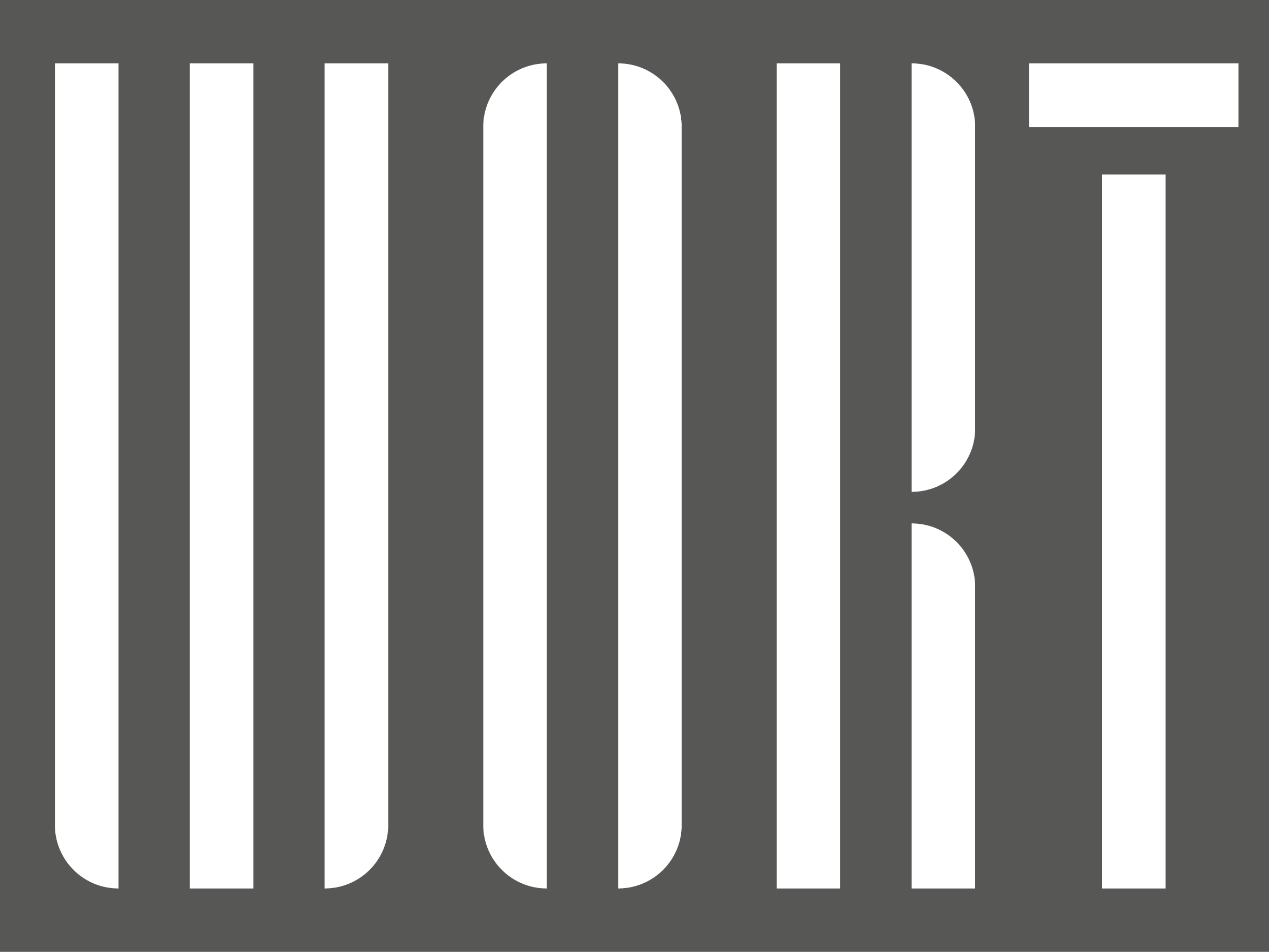
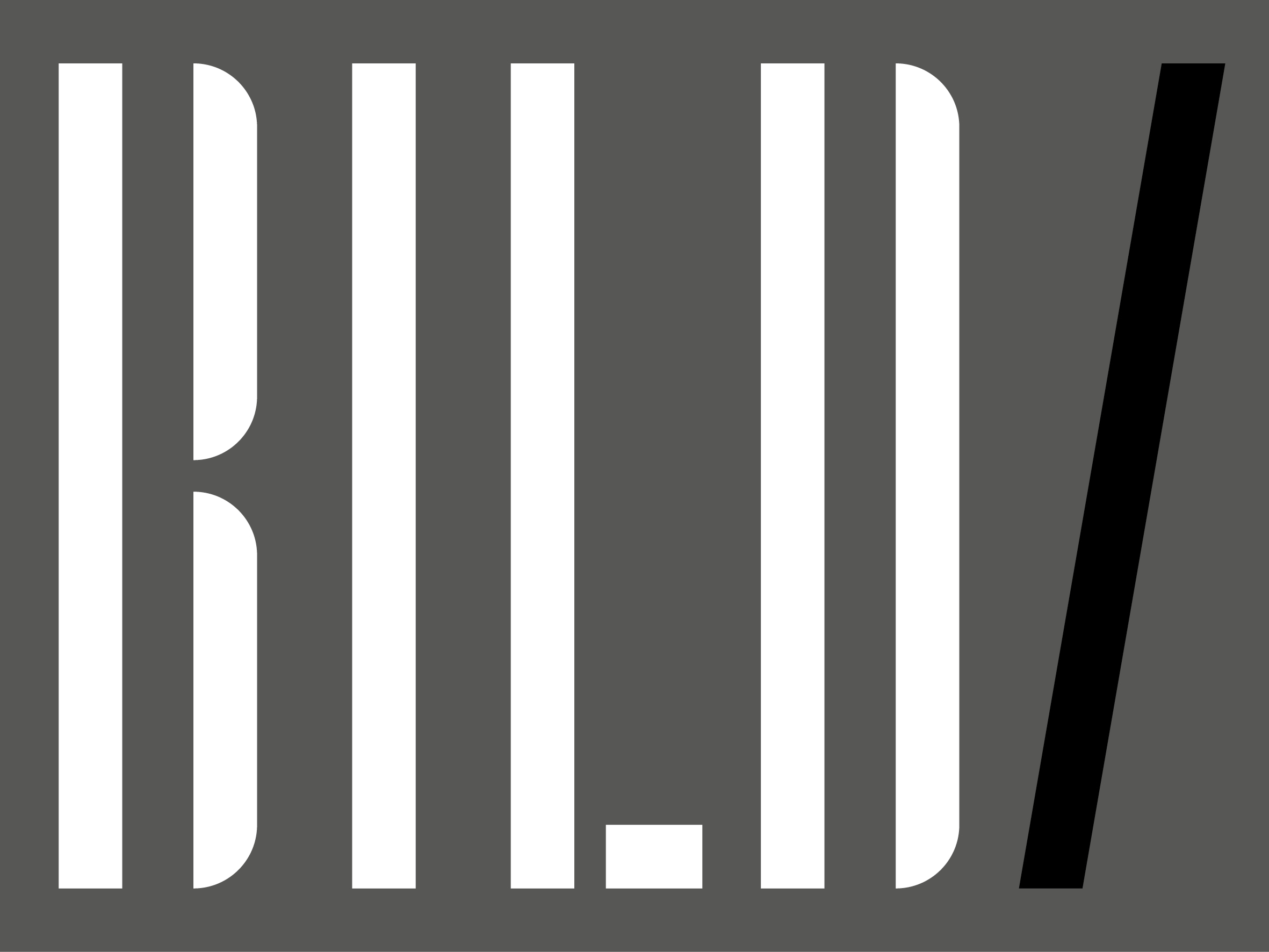
Typografische Selbstverwaltung (Typo-Club #19)
Typographic Self-Management (Typo Club #19)
Die Rolle des Lehrenden beschränkt sich in diesem Kurs auf das Fragenstellen, er darf nichts erklären, keine Antworten liefern – das ist den Studierenden überlassen. Je nach Anzahl der Teilnehmer*innen bilden sich kleine Gruppen, die selbstständig eine Einheit vorbereiten und präsentieren. Auch die praktische Aufgabe obliegt der Entscheidung der Studierenden. Es wird Protokoll geführt, eine Dokumentation der Veranstaltung erstellt und auf dem Rundgang präsentiert. Ziel ist eine genuin studentsiche Perspektive des Faches Typografie bei uns an der UdK Berlin.
The role of the teaching person is reduced to asking questions in this course, neither will he allow himself to explain anything or deliver any answers—that is left to the students. Depending on the amount of participants, small groups are formed who will prepare and present a unit each. The practical tasks are also decided upon by the students. A journal/log will be kept, and a documentation is presented at the Rundgang exhibition. The aim is a genuine student perspective on typography as a subject here at Berlin University of the Arts.